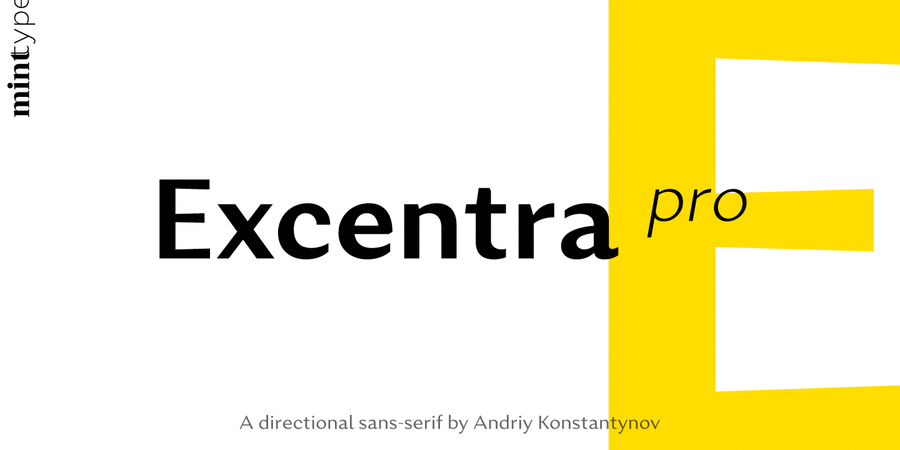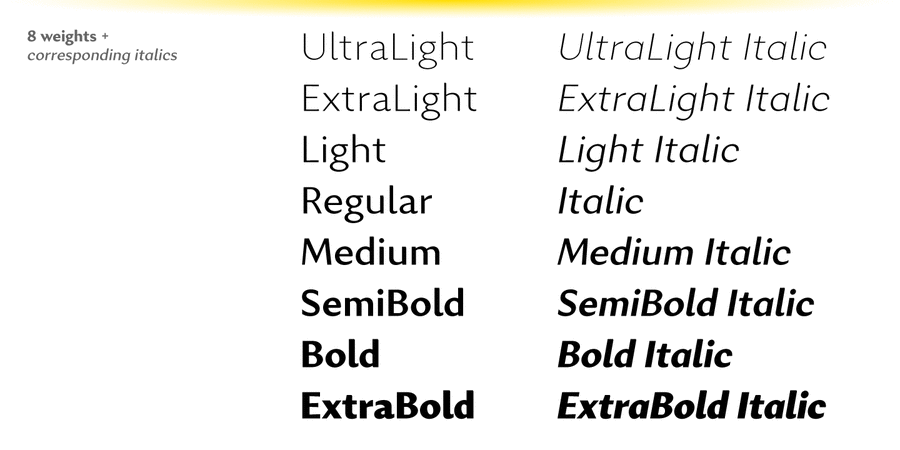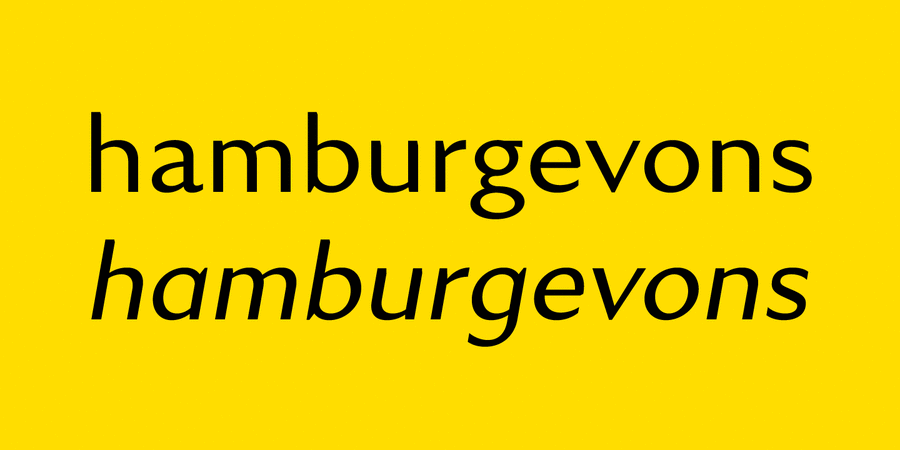
Excentra Pro – ґротеск, натхненний шрифтовими роботами з 1920-х, доповнений гуманістичної варіацією товщини штриху з нахиленою віссю. Специфічний елегантний малюнок робить Excentra Pro шрифтом для використання у журналах, брендінгу, а також у складанні великих масивів тексту. Гарнітура містить 8 насиченостей + курсив з підтримкою безлічі мов. Підтримка OpenType включає лігатури, капітель, 6 наборів цифр, верхні й нижні індекси, дроби, верхні літерні індекси для латинських рядкових, спеціалізований набір пунктуації для складання прописними та мовні альтернативи. Також включена підтримка прописної німецької Есцет.
Асоціації з сімейством шрифтів Excentra ProОсобистість і характер гарнітури:
тонкий, худий, витончений, холодний, делікатний, чистий, легкий, прохолодний, свіжий, модний, якісний, культурний, добірний, благородний, гармонійний, елітний, дорогий, розкішний, красивий, майстерний, знаменитий, оригінальний, багатий, сучасний, міський, прозорий, дротяний, естетичний, художній, освічений, елегантний, комільфо, сексуальний, ефектний, джентльменський, яскравий, виразний, пафосний, монументальний, серйозний, авторитетний, надійний, важливий, твердий, гордий, чіткий, артистичний, ексцентричний, претензійний, переконливий, сильний, смачний, апетитний, впевнений, урочистий, помітний
парфумерія, дієта, туалетна вода, шампунь, срібло, гігієна, розкіш, люкс, мода, чистота, ресторан, комільфо, музей, бутік, дизайн, годинник, парфуми, здоров'я, преміум, готель, шоколад, сервіровка, банкнота, монета, архітектура, архітектор, меморіал, пам'ятник, скульптура, кава, чай, фарба, алкоголь, Трофей, нагорода, кафе, взуття, обід, вечеря, їжа, цукерки, розваги, бар Гарнітура має ознаки стилів: